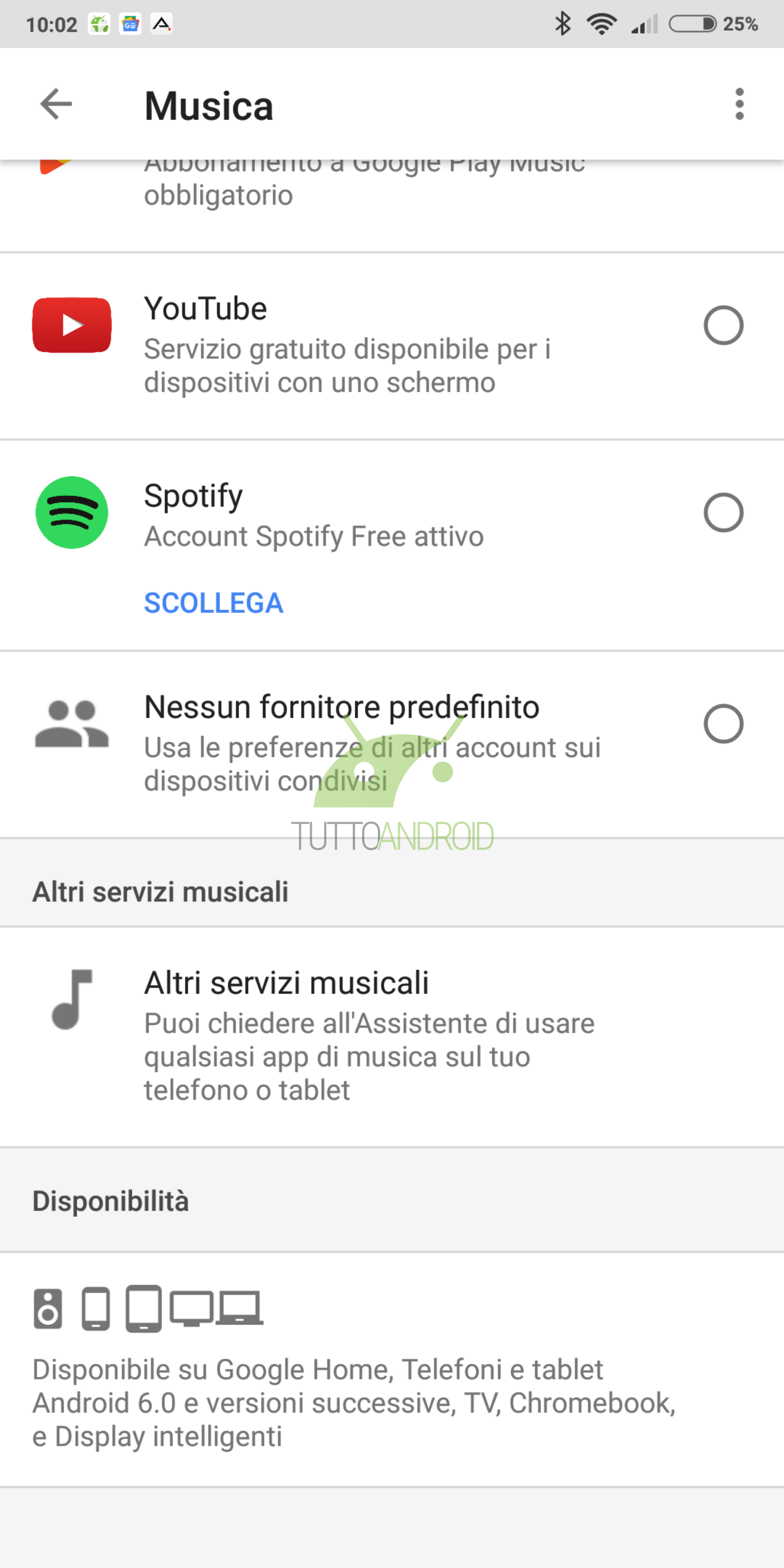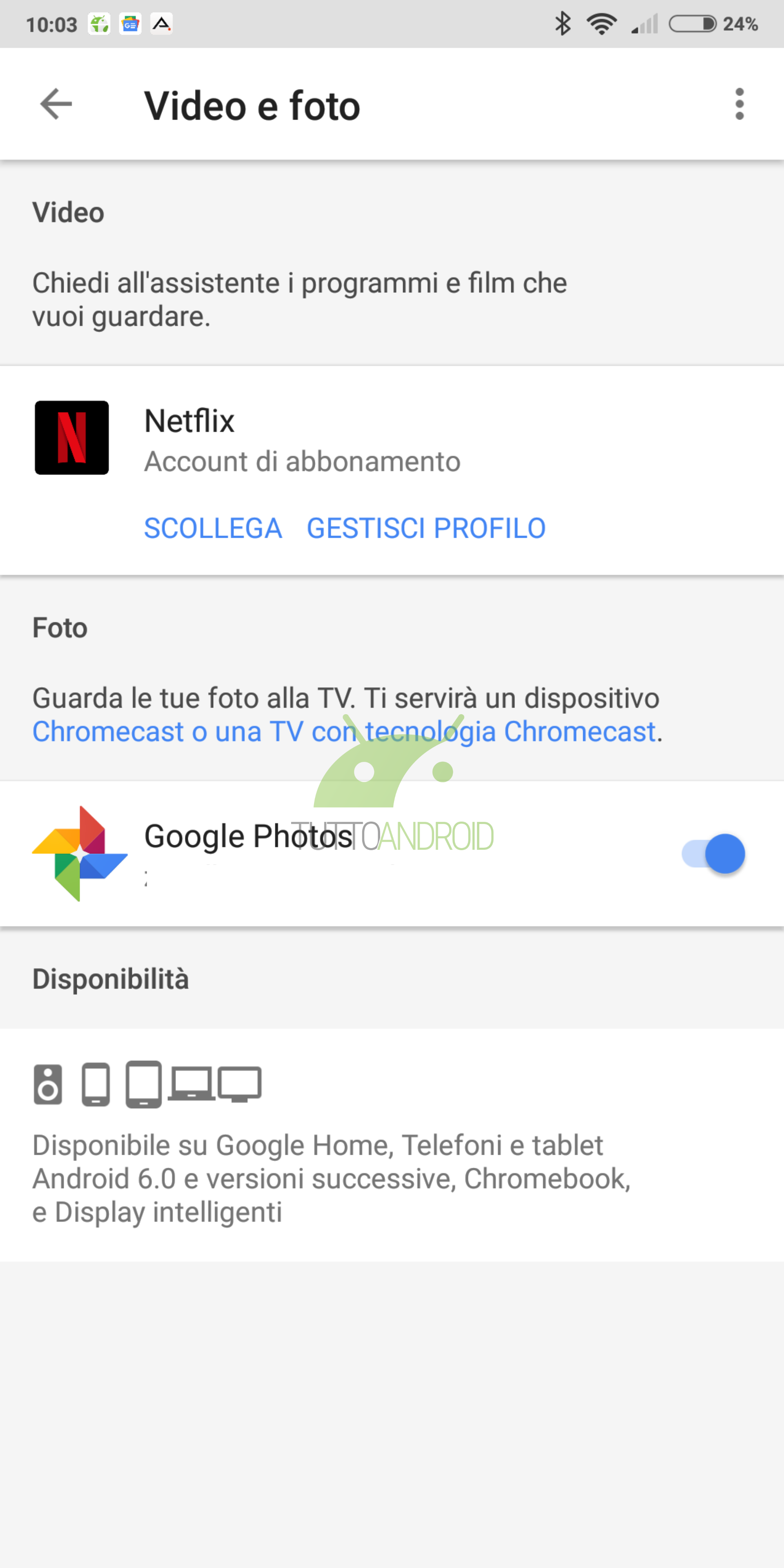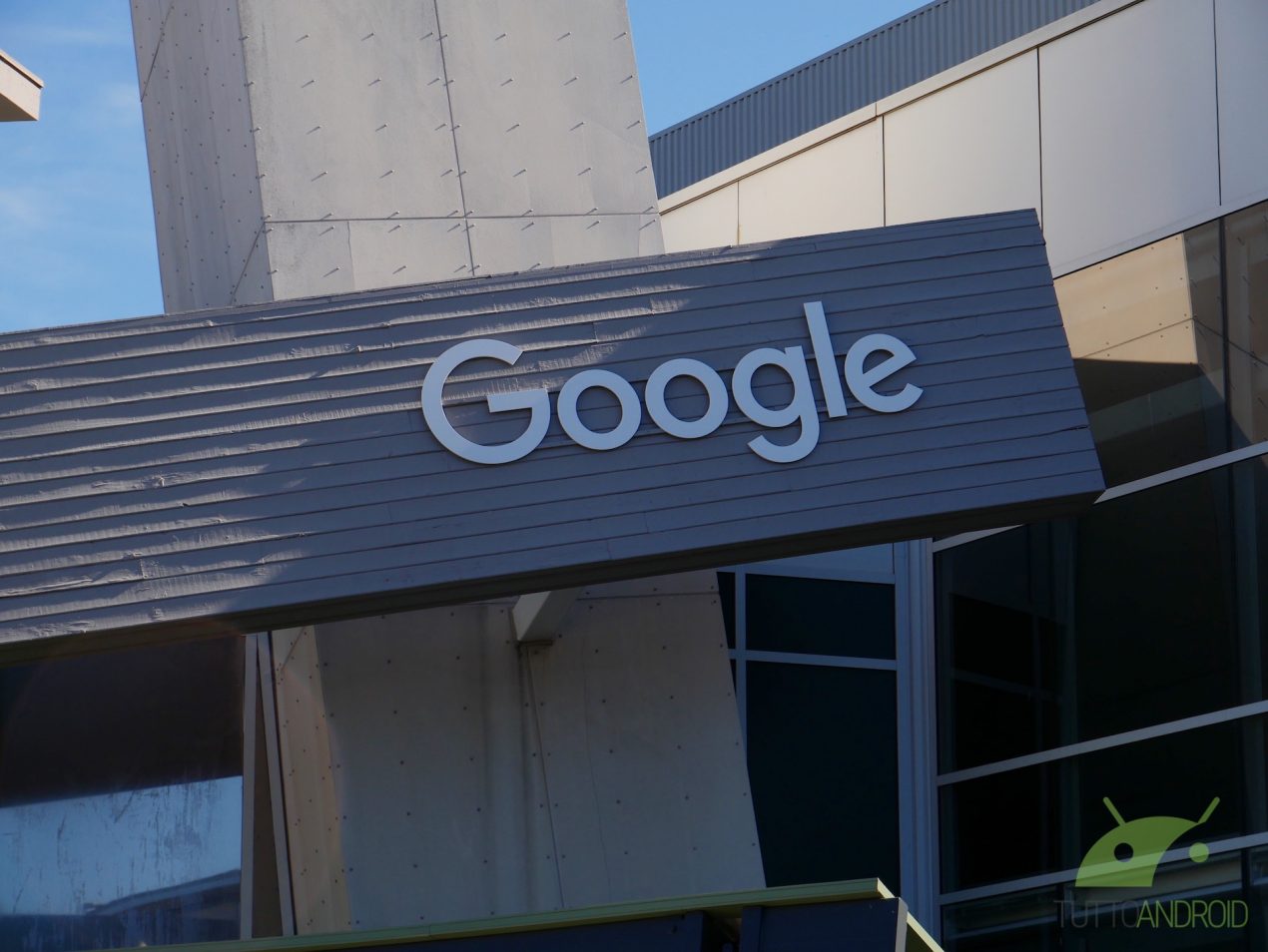
Il nuovo Material Theme, introdotto da Google al recente Google I/O 2018, sta rapidamente prendendo piede nelle varie applicazioni del colosso di Mountain View e con esso, almeno in parte anche il nuovo font Google Sans.
Il font, una leggera modifica rispetto a Product Sans, utilizzato per il logo di Big G, è ottimizzato per il funzionamento in diverse dimensioni ed è attualmente in fase di test A/B nei risultati delle ricerche. Al momento il carattere viene utilizzato solamente per i titoli delle pagine mentre il resto del testo utilizza il classico font Helvetica.